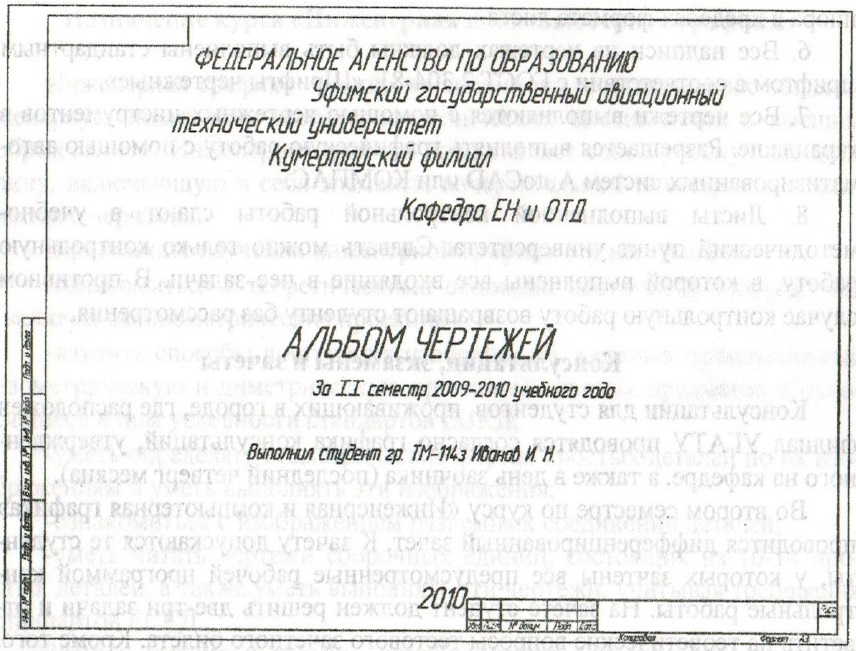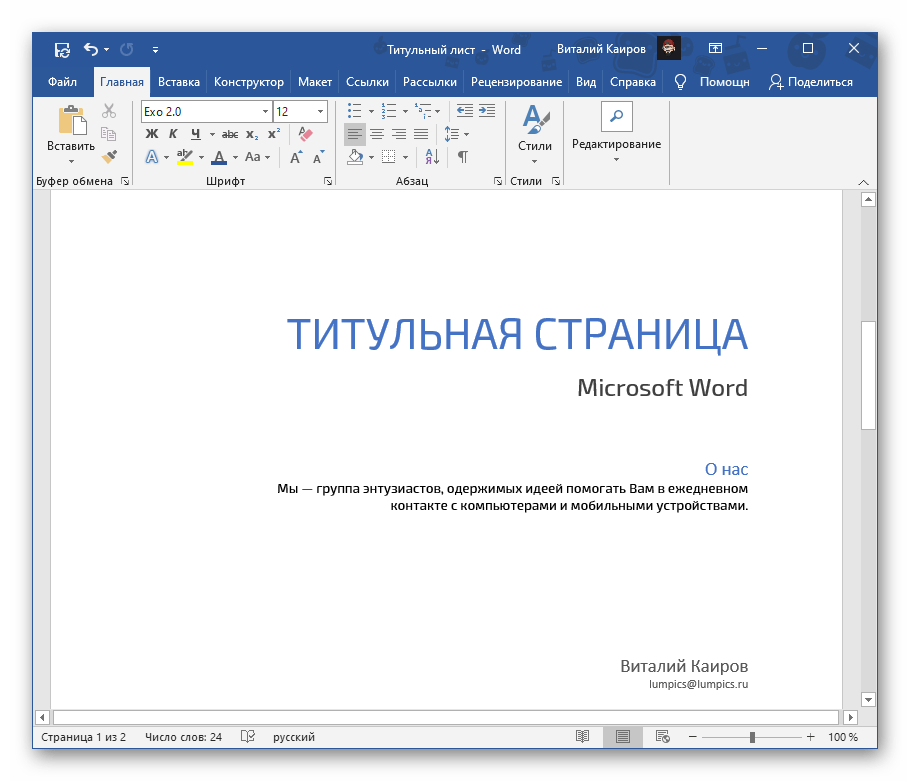
ТИТУЛЬНЫЙ лист
Рукописная книга не имела титульного листа. Не знали его и
первопечатные книги (инкунабулы), перенявшие традиции оформле¬
ния рукописной книги. Сведения об авторе книги, печатнике, месте и
времени издания помещались тогда в конце книги и назывались коло¬
фоном. Этот колофон, часто печатавшийся красной краской, можно
сравнить с выходными сведениями в наших книгах, хотя по содер¬
жанию они несколько отличаются (стр. 212). В дальнейшем колофон
перемещается из конца книги в ее начало, на первую страницу, со¬
ставляя название книги. Под этим названием-титулом начинался с
инициала текст. Но уже в конце XV века встречаются отдельные
книги, титульные листы которых свободны от основного текста. Один
из первых титульных листов такого типа принадлежит немецкому
печатнику Петеру Шефферу. Реформа титула была проведена в
начале XVI века.
Первые титульные листы были наборными, причем первая
строка титула набиралась обычно прописными буквами (версалем).
Позже, когда для набора титульных элементов книги стали отливать
специальные шрифты, титульный лист часто оформлялся таким об¬
разом, что первые строки заглавия набирались самыми крупными
шрифтами, а размер шрифта в последующих строках постепенно
уменьшался книзу страницы. Названия старинных книг были длин¬
ными, и титульный текст получал самую разнообразную форму, на¬
пример, треугольника, кубка и т. п. (стр. 213). Эмблема печатника и
декоративные украшения, воспроизводившиеся ксилографией, а позже
и гравюрой на меди, почти всегда сопутствовали шрифту на титуль¬
ном листе. Применение линеек, виньеток и орнаментов, отлитых из
оформление титульных листов. На заре книгопечатания особенно ши¬
роко использовался рамочный орнамент. Он занимал значительную
часть титульного листа и часто доминировал над его текстом. При
дальнейшем развитии специальных титульных шрифтов роль укра¬
шающих элементов на титуле значительно упала.
Надо сказать, чтостаринный титул с длинным текстом, набранным шрифтами разного
размера, со многими инициалами и орнаментикой, был сложным и
трудно читаемым. Однако, именно в этот период шло становление
отходя от своего рукописного прообраза, печатная книга обрела, на¬
конец, свои специфические черты — стала более простой по оформле¬
нию и легкой по восприятию, доступной широким слоям населения.
Искусство книги, и в частности оформление титульного листа
тесно связаны с художественными стилями и течениями, господство¬
вавшими в изобразительном искусстве каждой эпохи. Крупный
шрифт, античная ясность и соразмерность частей в композиции харак¬
терны, например, для титульного листа в период ренессанса. Барокко
и рококо перенасытили титул игривым орнаментом, внесли пышность
Знаменитые книгоиздатели XV—XVIII вв.
— Мануций, Эльзе¬
вир, Плантен, Дидо, Бодони и многие другие, создавшие много шедев¬
ров печатного искусства, довели набор титульных листов до высокой
степени совершенства. В России наборный титул достиг наивысшего
расцвета в первой половине XIX века в типографиях Селивановского,
Бекетова, Смирдина, Семена.
Во второй половине XIX века, в связи с общим упадком буржу¬
азного искусства, мельчает и искусство оформления книги. Титуль¬
ные листы набираются вычурными, малохудожественными шрифтами
глубокого упадка типографского искусства конца XIX века У. Мор-
14«
Виды и оформление титульного листа . Оформление книги. Редактору и автору
Обычно титул бывает однополосным, то есть располагается на одной странице. Но в некоторых изданиях помещают двухполосный титул, занимающий две смежные страницы книжного разворота. Он подчеркивает большую значимость издания, его капитальность.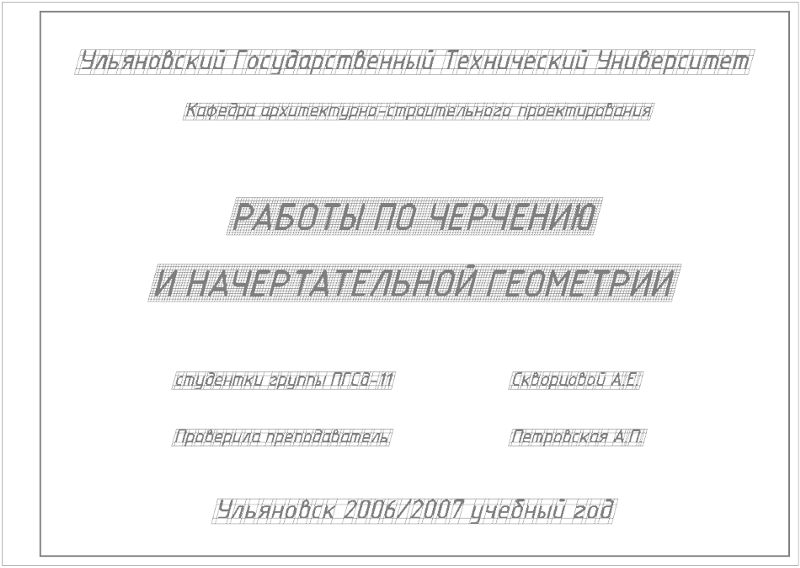
77. Разворотный титульный лист в многотомном издании: полосы построены асимметрично и неодинаково загружены
Существуют два основных варианта двухполосного титула. В одном варианте каждая полоса представляет собой законченную, в какой-то мере самостоятельную часть общей композиции (рис. 77). Такой вариант часто применяется в многотомных и серийных изданиях. На левой странице разворота, так называемом контртитуле, могут быть помещены сведения, относящиеся ко всему изданию или ко всей серии в целом, а на правой странице — основном титуле — сведения о данном томе (возможны и другие варианты). Подобный титул может быть дан и в переводном издании. При этом слева помещается титул на языке подлинника, справа — на языке перевода. Такого рода титул часто называют разворотным.
В другом варианте композиция двухполосного титула представляет собой единое, неразрывное целое, текст и изобразительные элементы начинаются на левой странице разворота и заканчиваются на правой, часто захватывая и корешковые поля (рис.
Иногда в малообъемных брошюрах, рассчитанных на недолгий срок пользования, для экономии бумаги вместо титульного листа помещают титул-шапку. Такой прием часто практикуется в журналах.
Чтобы титул хорошо воспринимался читателем, необходимо из всех помещенных на нем разнообразных и неодинаковых по значению сведений выделить важнейшие, сделать явной связь между ними, выявить их соподчинение и единство. Все это достигается прежде всего соответствующим подбором шрифтов, логичной группировкой строк и их обоснованным расположением.
4. Trade Gothic
Trade Gothic — универсальный шрифт без засечек, представленный в нескольких стилях и размерах.
Во-первых, необходимо иметь понимание своего намерения. Стоит изучить популярные шрифты и узнать, где они используются и как воспринимаются. Имея так много доступной информации, было бы неразумно не принимать обоснованные решения о шрифтах. Некоторые люди будут сильно относиться к определенным типам или отдавать предпочтение шрифтам с засечками, а не без засечек. Это действительно должно хорошо сочетаться с намерением или общим проектом.